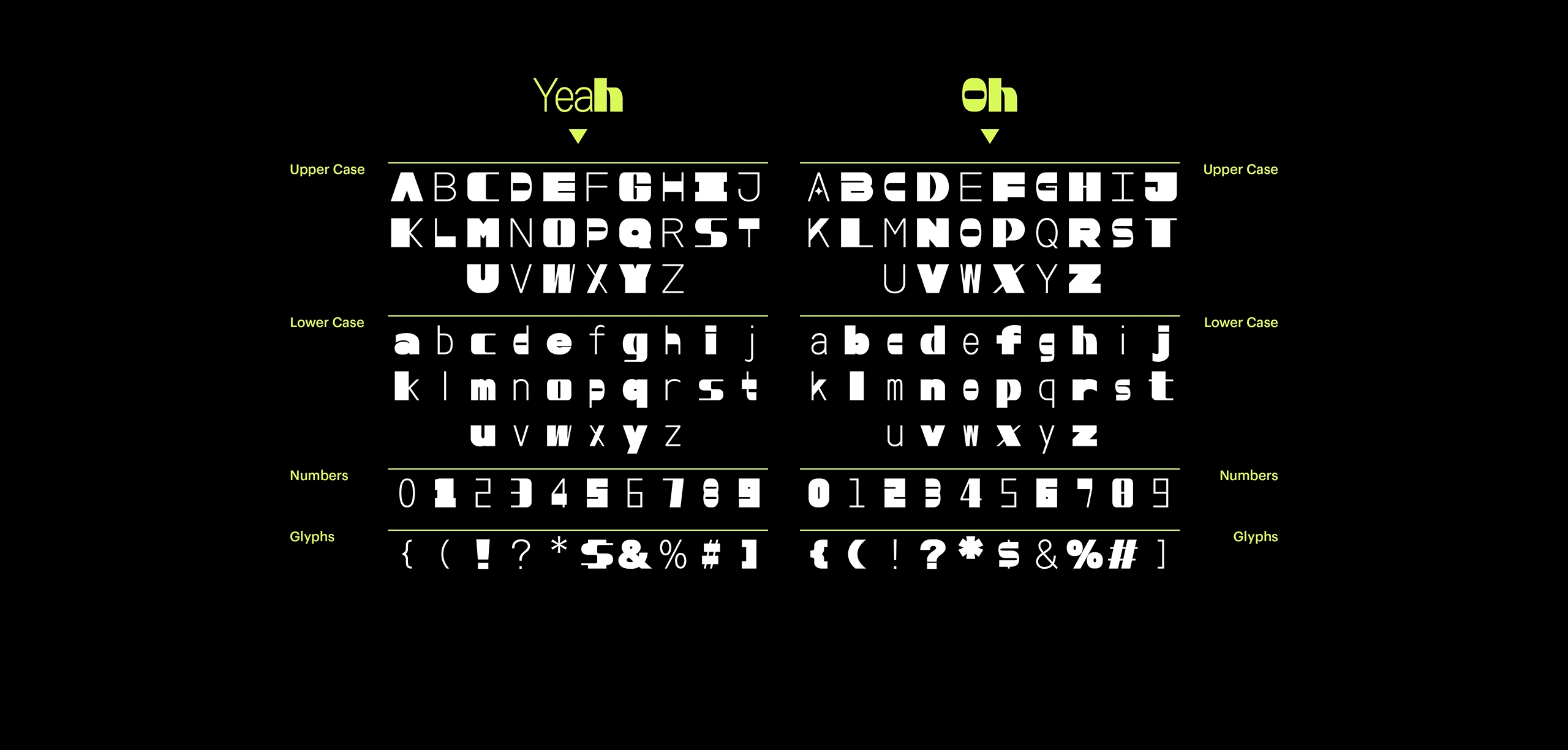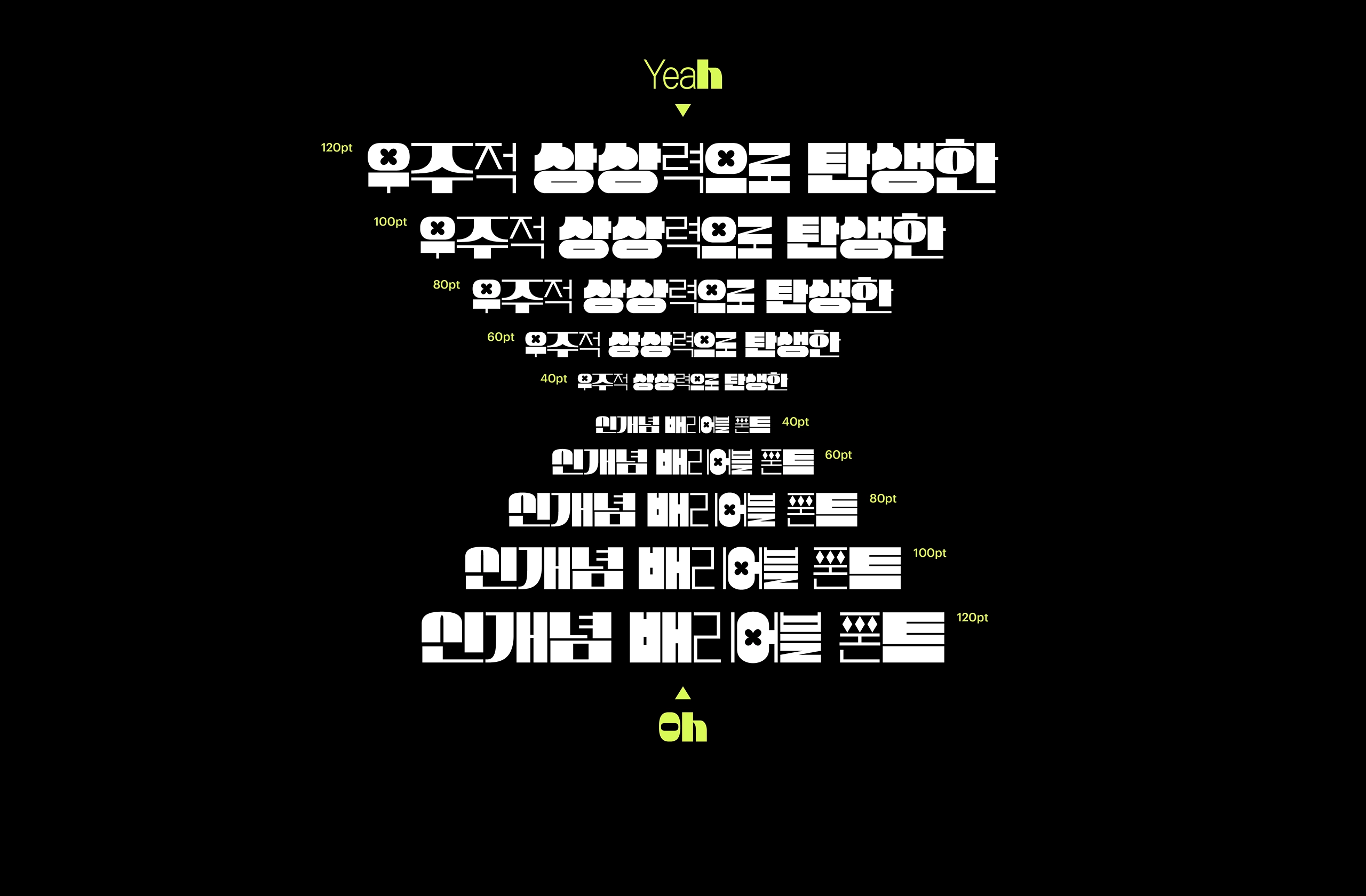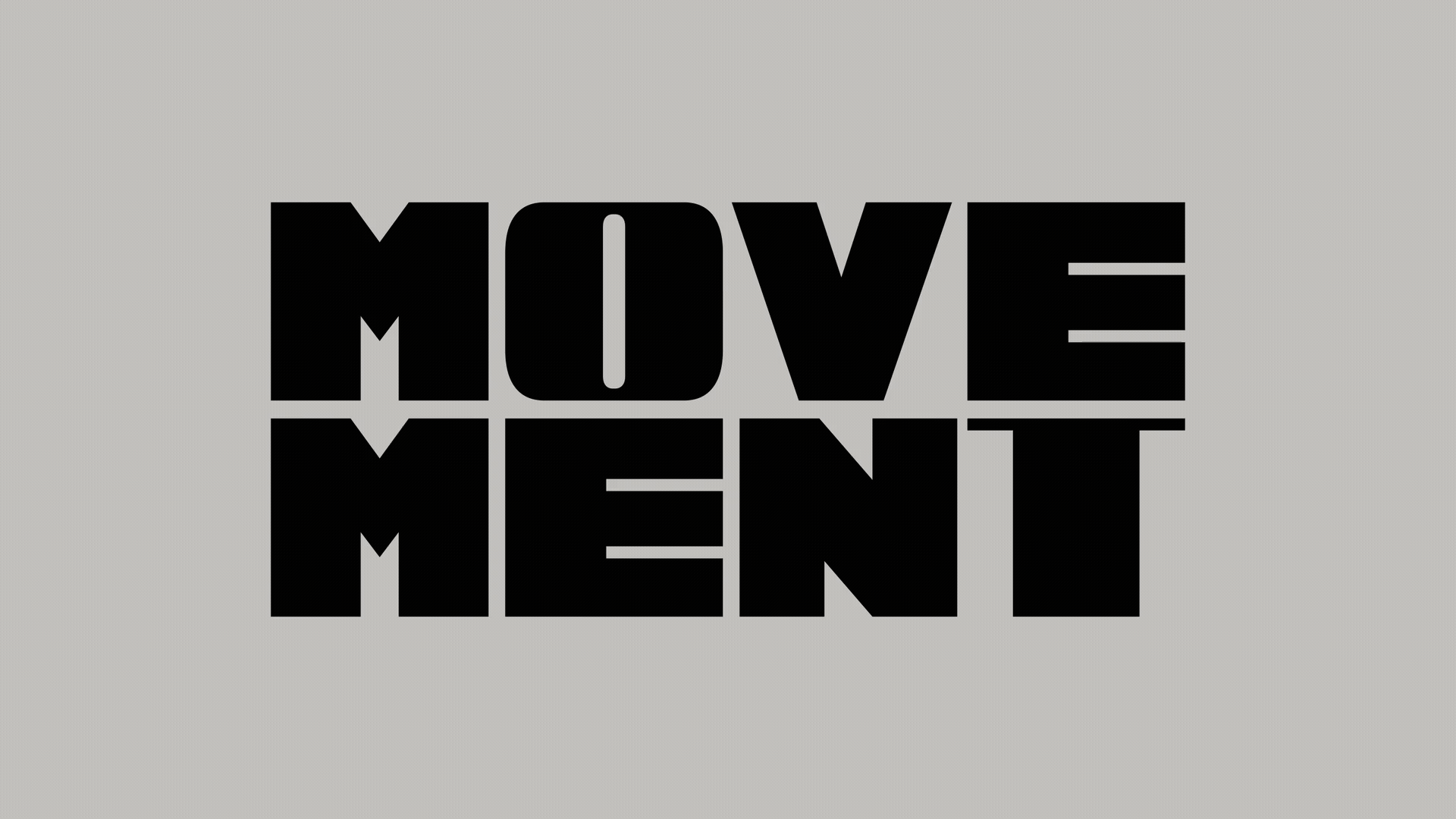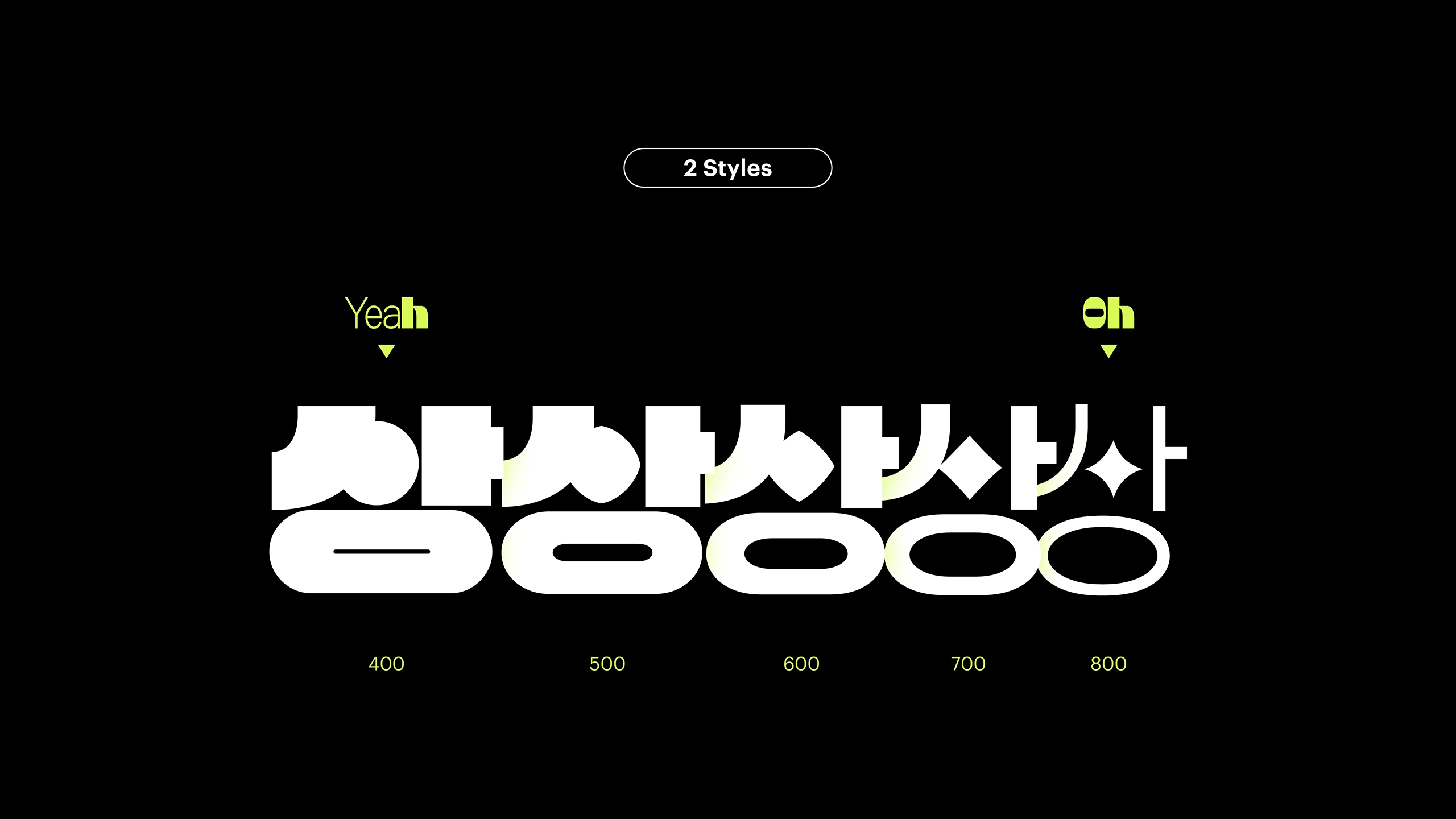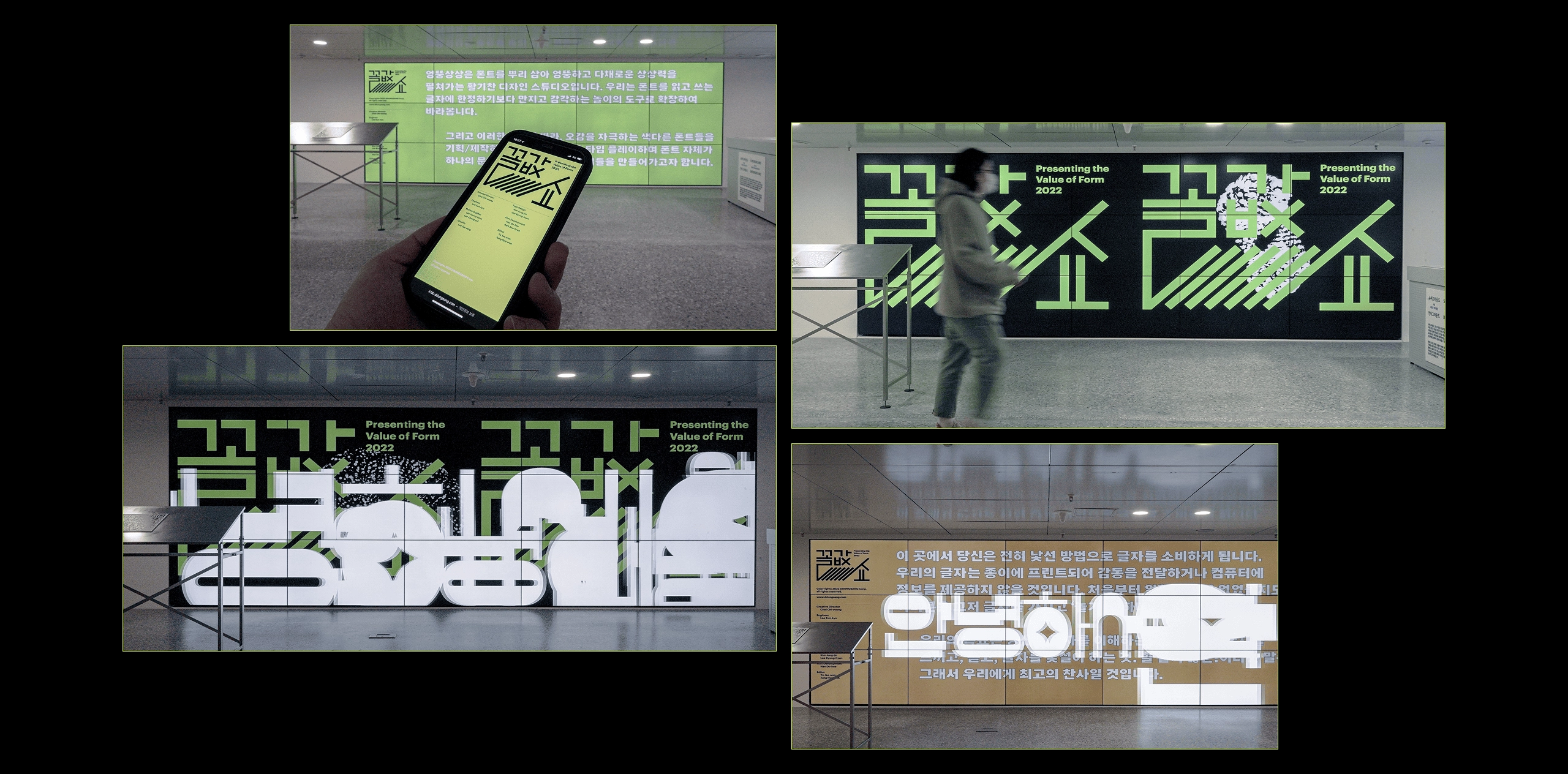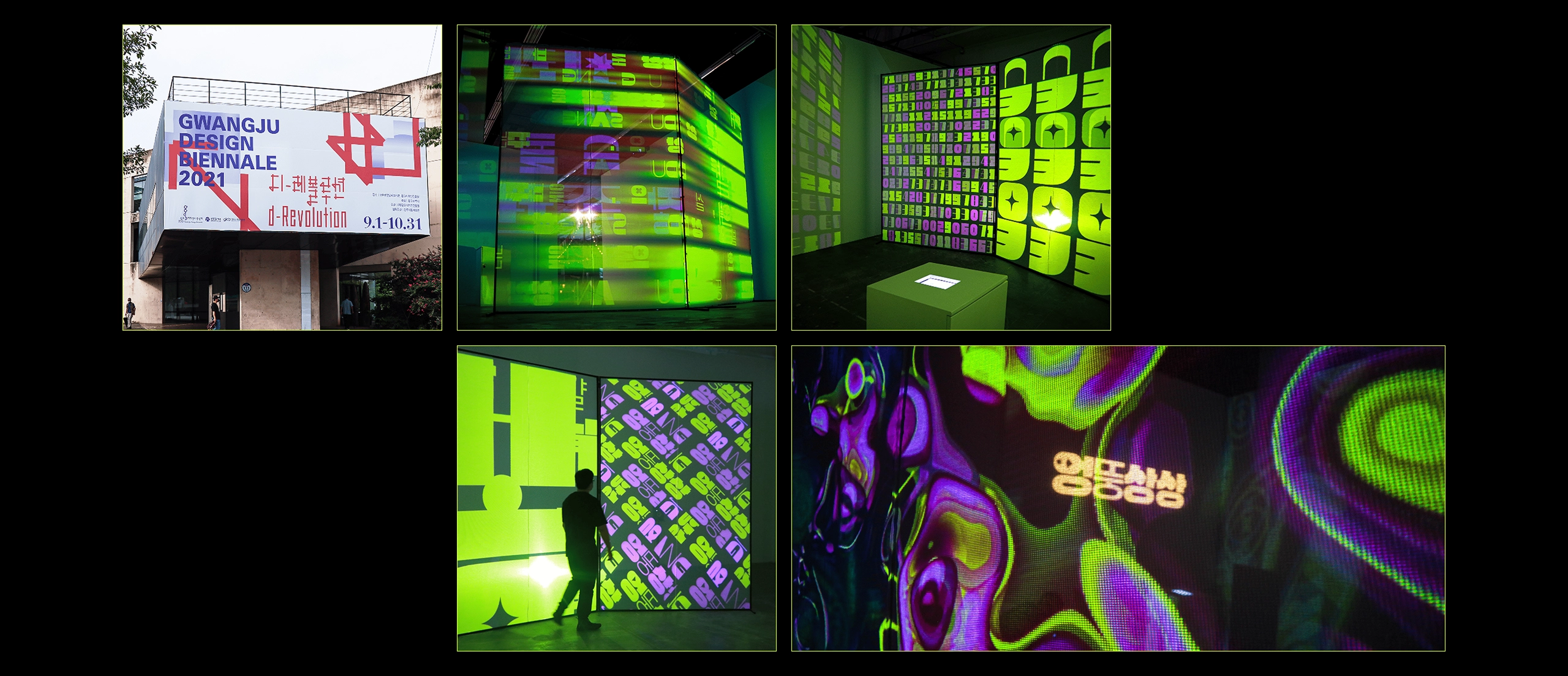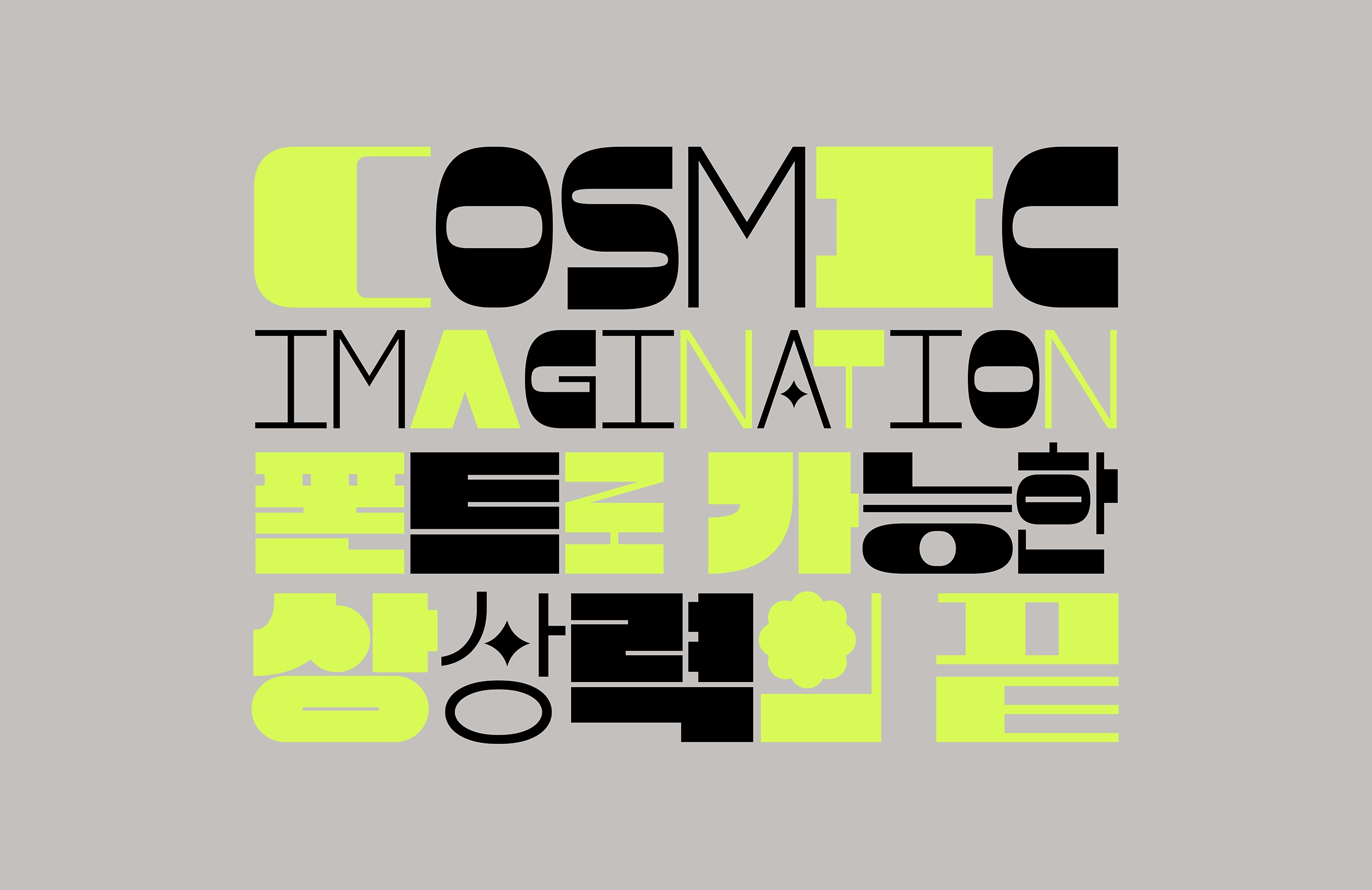
엉뚱상상체는 폰트로 가능한 상상력을 저 끝까지 밀어붙여 제작해본 실험적인 폰트입니다. 무엇을 상상하든 그 이상! 오감을 자극하는 화려한 배리어블 축제가 펼쳐집니다.
엉뚱상상은 폰트를 뿌리 삼아 엉뚱하고 다채로운 상상력을 펼쳐가는 활기찬 디자인 스튜디오입니다. 우리는 폰트를 읽고 쓰는 글자에 한정하기보다 만지고 감각하는 놀이의 도구로 확장하여 바라봅니다. 그리고 이러한 관점에 따라, 오감을 자극하는 색다른 폰트들을 기획·제작하고 다양한 방식으로 타입 플레이하며 폰트 자체가 하나의 문화를 표상할 방법들을 만들어가고자 합니다.
레터빌런 (이상민, 김정진, 김민주, 이병헌)
디자이너 소개
레터빌런은 2021년 결성된 4인조 서체 디자인 그룹으로, 파격적인 한글 디자인을 통해 다음 세대에 타이포그래피에 대한 개념을 고민하고 제안하는 글자를 디자인합니다.
폰트로 펼칠 수 있는 가능성의 끝은 어디일까요?
엉뚱상상Variable은 평범함을 거부하는 범우주적 상상력으로 완성해낸 신개념 배리어블 폰트입니다.
색다른 움직임으로 오감을 자극하는 엉뚱상상Variable만의 바이브에 몸을 맡겨보세요.
얼터너티브 문화를 만들어가는 브랜드, 크리에이터들에게 영감을 주는 선물이 되기를 기대합니다.
엉뚱상상과 레터빌런은 2021년 광주디자인비엔날레 <2021 꼴값쇼: 레터빌런의 침공>과
2022년 서울도시건축전시관 <2022 꼴값쇼> 전시를 통해
엉뚱상상Variable을 처음 선보였습니다.
광주디자인비엔날레
<2021 꼴값쇼: 레터빌런의 침공>
서울도시건축전시관
<2022 꼴값쇼>